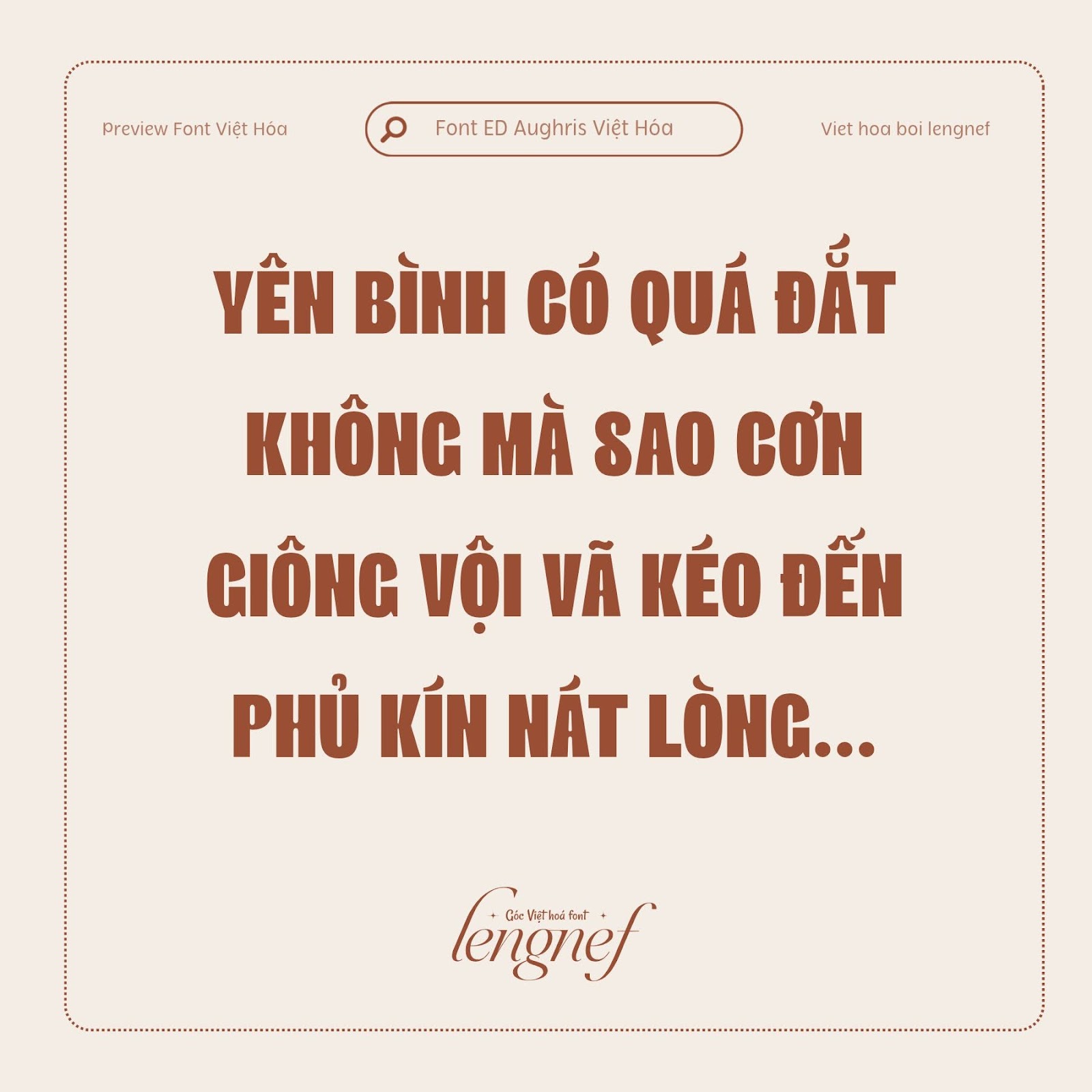
LF ED Aughris
- Tác giả: Emyself Design
- Việt hóa: lengnef
ED Aughris là một phông chữ sans-serif hiển thị với đặc điểm mạnh mẽ và hiện đại. Kiểu chữ đậm nét và phong cách tối giản của nó giúp phù hợp với nhiều thiết kế khác nhau từ tiêu đề đến các yếu tố đồ họa nổi bật.
Phong cách hiện đại và tối giản của ED Aughris cũng rất phù hợp với các xu hướng thiết kế hiện nay. Phông chữ này sẽ mang đến cho thiết kế của bạn một diện mạo tươi mới và hiện đại. Phông này chỉ có kiểu chữ in hoa nên dùng kết hợp với các font mảnh khác để làm nổi bật thiết kế hơn.